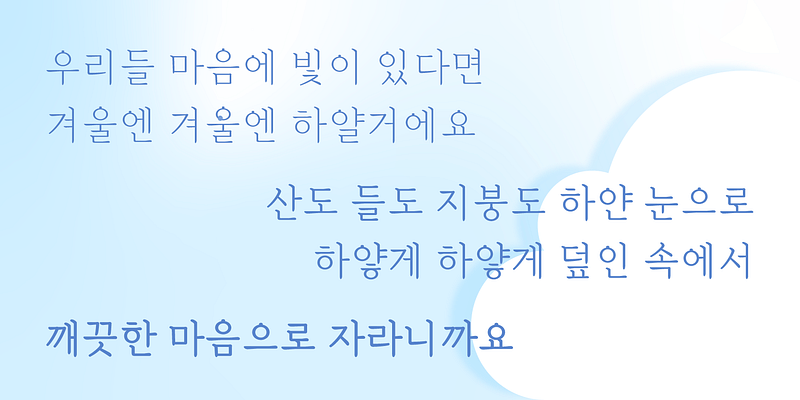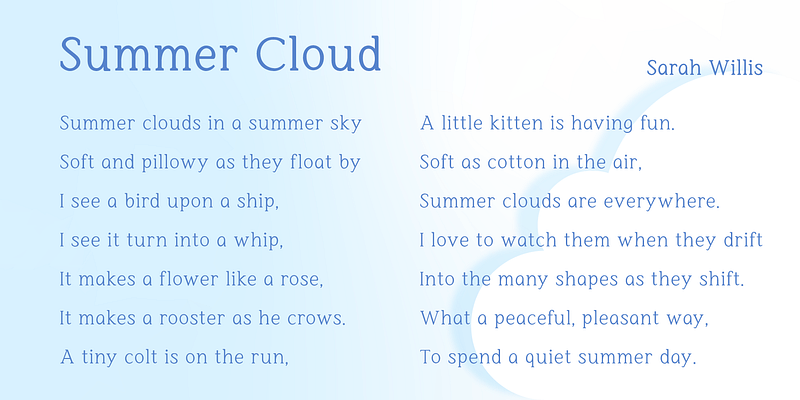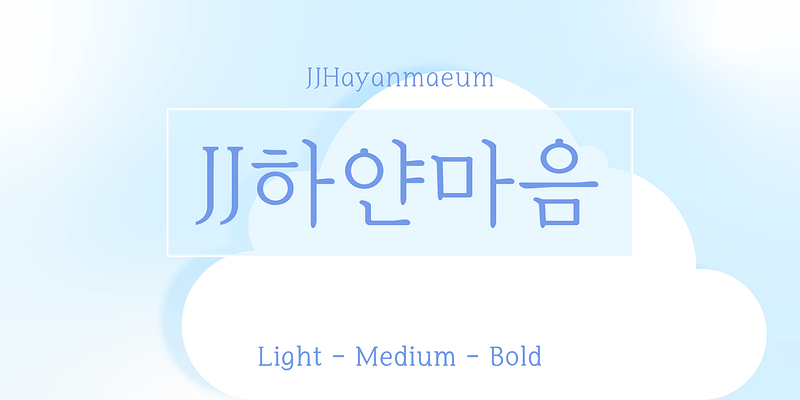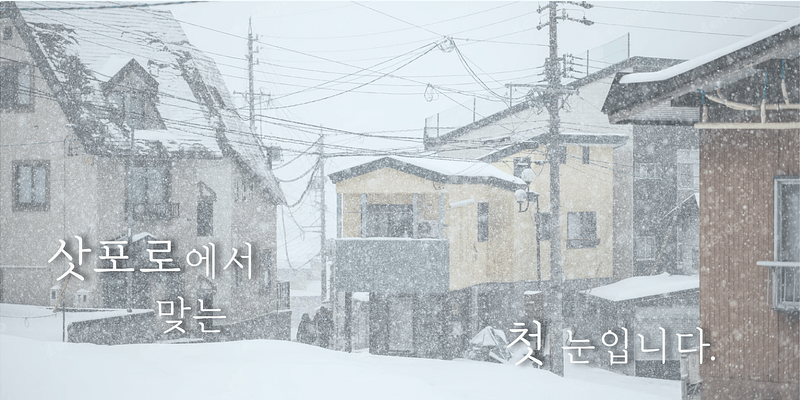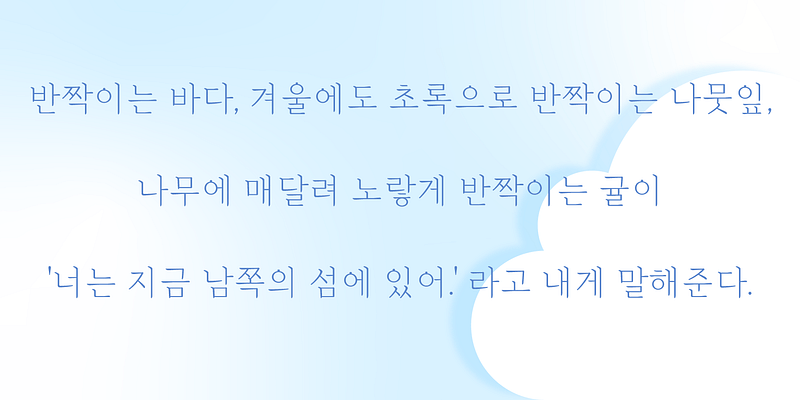
Mit ihren feinen Serifen und Linien, die in eine Myeongjo-Struktur eingebettet sind, wirkt die Schrift „White Heart“ modern und minimalistisch. Die Schrift wurde für optimale Lesbarkeit auf verschiedenen Medien entwickelt und zeichnet sich durch eine klare und einladende Ästhetik aus.